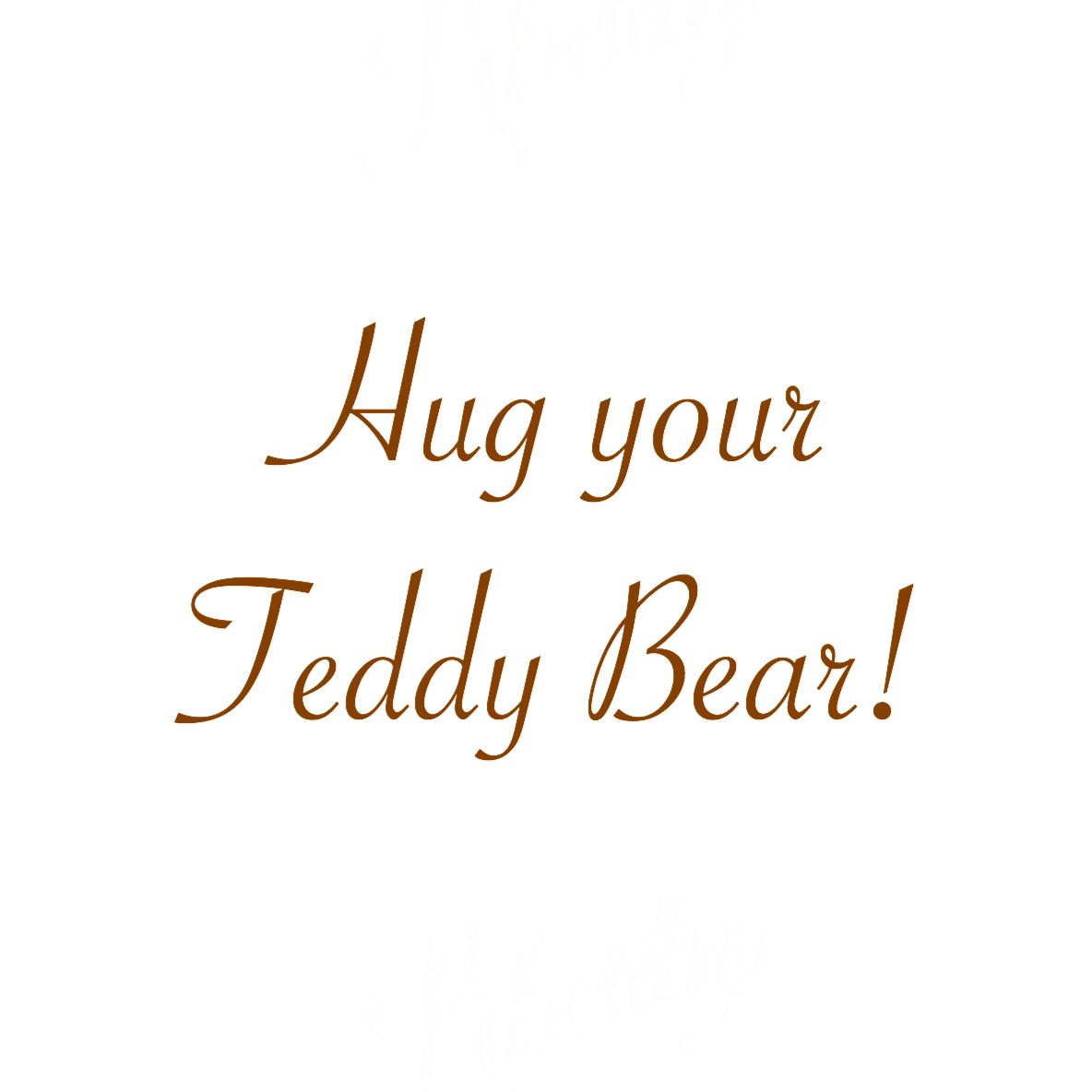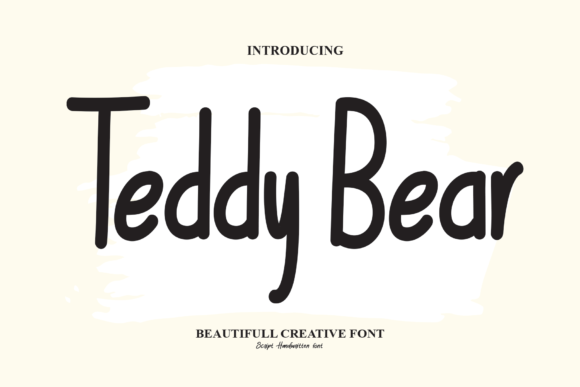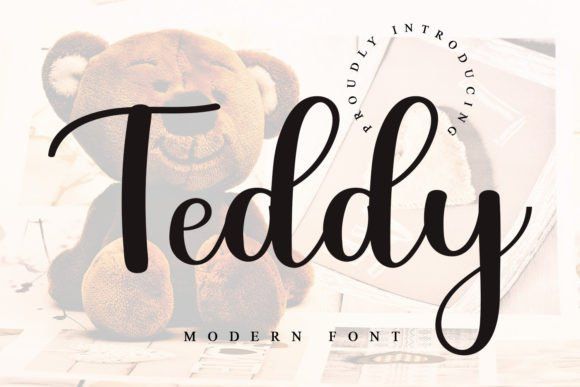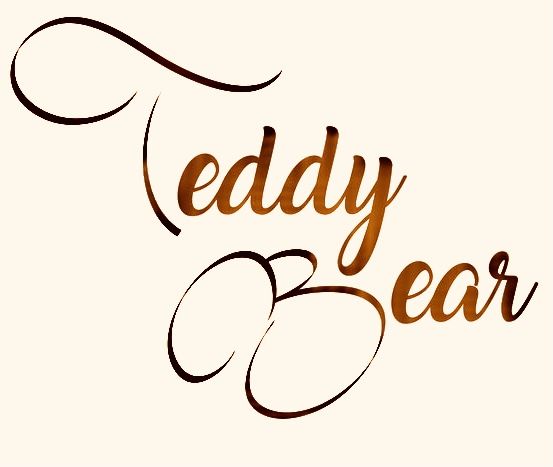
147 Font Teddy Bear – Tải font chữ dễ thương, mềm mại và đáng yêu
Font Teddy Bear là bộ phông chữ thuộc dòng Display mang phong cách mập mạp, dễ thương và ấm áp, được thiết kế mô phỏng lại sự mềm mại, ngộ nghĩnh của những chú gấu bông. Với cấu trúc nét chữ căng tròn, phúng phính và tràn đầy sự thân thiện, nhóm phông chữ này là lựa chọn số một cho các thiết kế bao bì đồ chơi trẻ em, hộp bánh quy bơ, nhãn dán sản phẩm mẹ và bé và các ấn phẩm quà tặng ngọt ngào. Doozypack.vn cung cấp link tải Font Teddy Bear Việt hóa chuẩn kỹ thuật, giúp bạn sở hữu phông chữ đáng yêu này mà không lo gặp bất kỳ lỗi hiển thị dấu thanh nào khi thiết kế in ấn.
Đặc điểm thẩm mỹ độc đáo của Font Teddy Bear
Font chữ Teddy Bear không đi theo sự sắc nhọn của các phông chữ hình học; nó mang đến một ngôn ngữ thị giác đầy ắp sự êm ái, gợi nhắc đến cảm giác ôm ấp và sự an toàn.
Mẫu chữ Teddy Bear dễ thương
Phong cách Puffy & Bubbly ngộ nghĩnh và ấm áp
Đặc trưng lớn nhất của Font chữ Teddy Bear là hình khối chữ cái phồng căng như được nhồi bông, tạo nên một sức nặng thị giác vô cùng ngộ nghĩnh. Các góc nối và điểm kết thúc nét đều được bo tròn tuyệt đối, mang lại cảm giác thân thiện, vô tư và cực kỳ gần gũi. Khi đặt phông chữ này làm tiêu đề trên bao bì, sản phẩm của bạn sẽ ngay lập tức thu hút ánh nhìn của các bạn nhỏ và tạo được thiện cảm tuyệt vời với các bậc phụ huynh.
Đường nét bo tròn mập mạp mang lại cảm giác thân thiện
Cấu trúc của Font Style Teddy Bear sở hữu độ dày nét (weight) cực lớn nhưng tỷ lệ khoảng hở trong chữ (counter) vẫn được duy trì vừa đủ để đảm bảo độ rõ đọc. Phông chữ này mang diện mạo vui tươi, giúp xua tan đi sự khô cứng của các thông tin kỹ thuật trên vỏ hộp, biến mỗi sản phẩm trở thành một món quà tinh thần đầy ý nghĩa.
Ưu điểm nổi bật của bản Font Teddy Bear Việt hóa
Khi ứng dụng các phông chữ trang trí mập mạp vào thị trường trong nước, sự chỉn chu về dấu câu là yếu tố quyết định đến tính chuyên nghiệp của ấn phẩm:
• Khắc phục triệt để lỗi dấu tiếng Việt: Phiên bản Font Teddy Bear Việt hóa đã được đội ngũ thiết kế trau chuốt thủ công từng dấu câu. Các dấu sắc, huyền, hỏi, ngã, nặng được vẽ căng mọng, bo tròn đồng điệu cùng thân chữ gốc, không gây cảm giác chắp vá hay đè nét làm mất tính thẩm mỹ.
Kiểu chữ mềm mại đáng yêu
03 Ứng dụng thực tế của font Teddy Bear trong sản xuất bao bì tại Doozypack.vn
Sự ngọt ngào và đáng yêu của Teddy Bear mang lại hiệu ứng thị giác đắt giá trên các dòng sản phẩm bao bì thực tế do Doozypack.vn sản xuất:
• Hộp giấy đựng Bánh quy & Kẹo ngọt (Bakery): Tiêu đề thương hiệu in bằng font Teddy Bear trên hộp bánh cookie tạo nên vẻ ngoài ngon miệng, ấm áp và gợi nhắc đến hương vị bánh nướng thủ công gia đình.
• Bao bì Đồ chơi trẻ em & Hộp quà sinh nhật: Nét chữ phồng căng ngộ nghĩnh thu hút sự chú ý của các bé ngay từ cái nhìn đầu tiên trên kệ hàng siêu thị.
• Tem nhãn dán Sticker & Nhãn sản phẩm Mẹ và Bé: Cấu trúc chữ thân thiện rất thích hợp để in các tem decal tròn dán lên bình sữa, hộp đựng đồ dùng hoặc túi quà tặng sơ sinh.
Thiết kế typography trẻ trung
• Kiểm soát hiện tượng tràn mực (Dot Gain) tại khe chữ nhỏ: Các khoảng hở bên trong chữ cái (như chữ ‘e’, ‘a’, ‘o’) khá hẹp. Khi in trên giấy có độ thấm mực cao như giấy Kraft, mực có thể bị lan làm bít kín các lỗ hở này. Bạn nên giữ size chữ tiêu đề tối thiểu từ 10pt trở lên để bảo đảm độ sắc nét.
• Lựa chọn hệ màu sắc rực rỡ hoặc Pastel: Phong cách Teddy Bear đẹp nhất khi phối với các tông màu Pastel nhẹ nhàng (hồng phấn, vàng kem, xanh mint) hoặc màu sắc rực rỡ tươi vui.